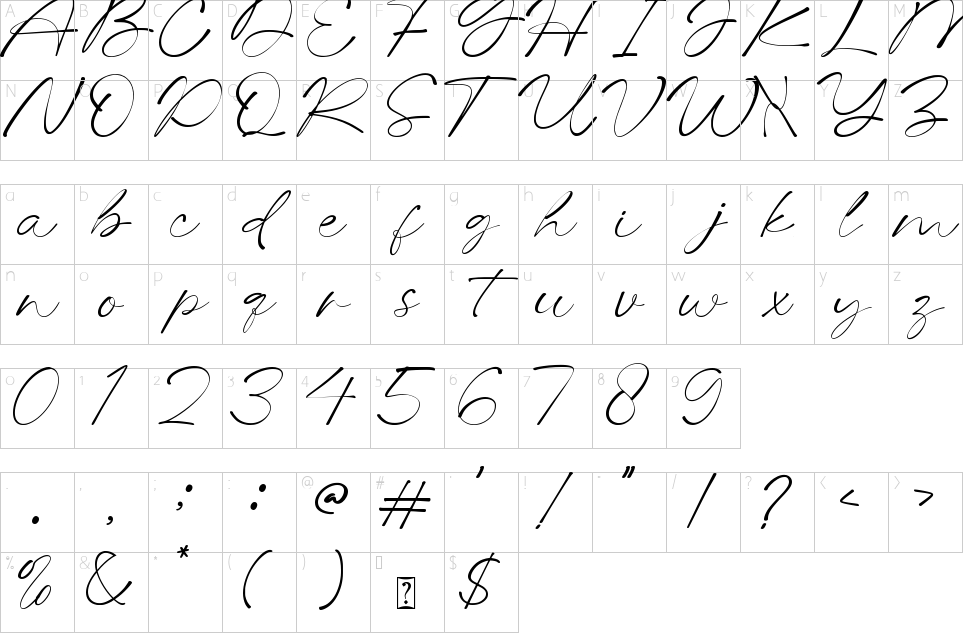
A Arveton Font é uma elegante escolha para designers e gráficos digitais em busca de uma fonte de qualidade para projetos variados. Desenvolvida pelo Letterara Studio, essa fonte vem da paleta de Letras Arquetônica, oferecendo uma gama de estilos e usos que vão do título ao texto. Com um design cuidadosamente elaborado, a Arveton é uma fonte para quem busca uma combinação perfeita de simplicidade e sofisticação. Seja para criar um layout minimalista ou para adicionar um toque criativo a um design, a Arveton atende perfeitamente às necessidades de qualquer designer. Com 280 downloads, essa fonte está ganhando cada vez mais seguidores e sua presença na categoria de fontes grátis confirma sua qualidade e sua relevância no mercado. Baixe já a Arveton Font para Windows e Mac e comece a experimentar o seu poder de personalização e beleza.